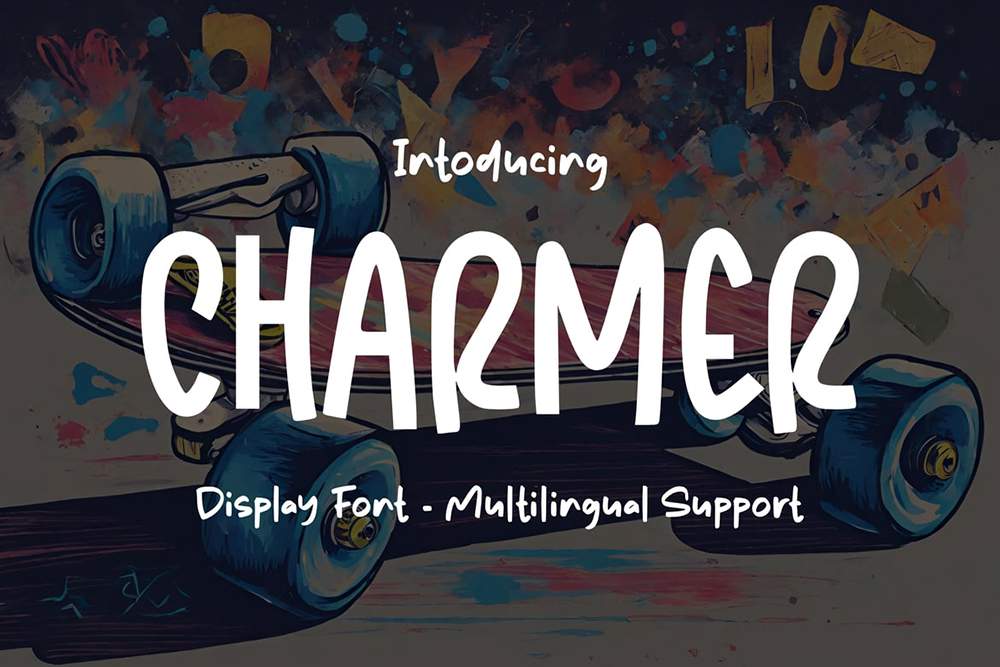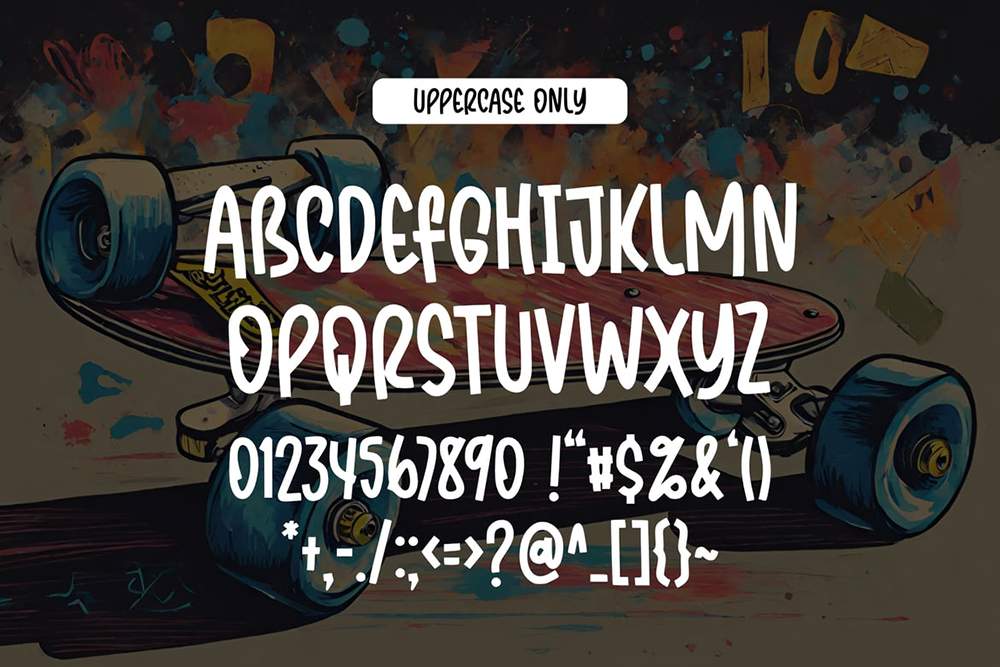
دانلود فونت انگلیسی Charmer Font
فونت پرمیوم و انگلیسی Charmer Font یک فونت جسورانه و شیک است که با حروف بزرگ و رسا در هر طرحی جذابیت و گرمی را به نمایش میگذارد و جلوهای قوی و جذاب برای عناوین فیلم، عناوین کتاب، زیرنویسها و طراحیهای دیگر ایجاد میکند. اين فونت برای هر پروژه برندسازی مانند لوگو و… مناسب است.
مزایای استفاده از فونت لاتین Charmer چیست؟